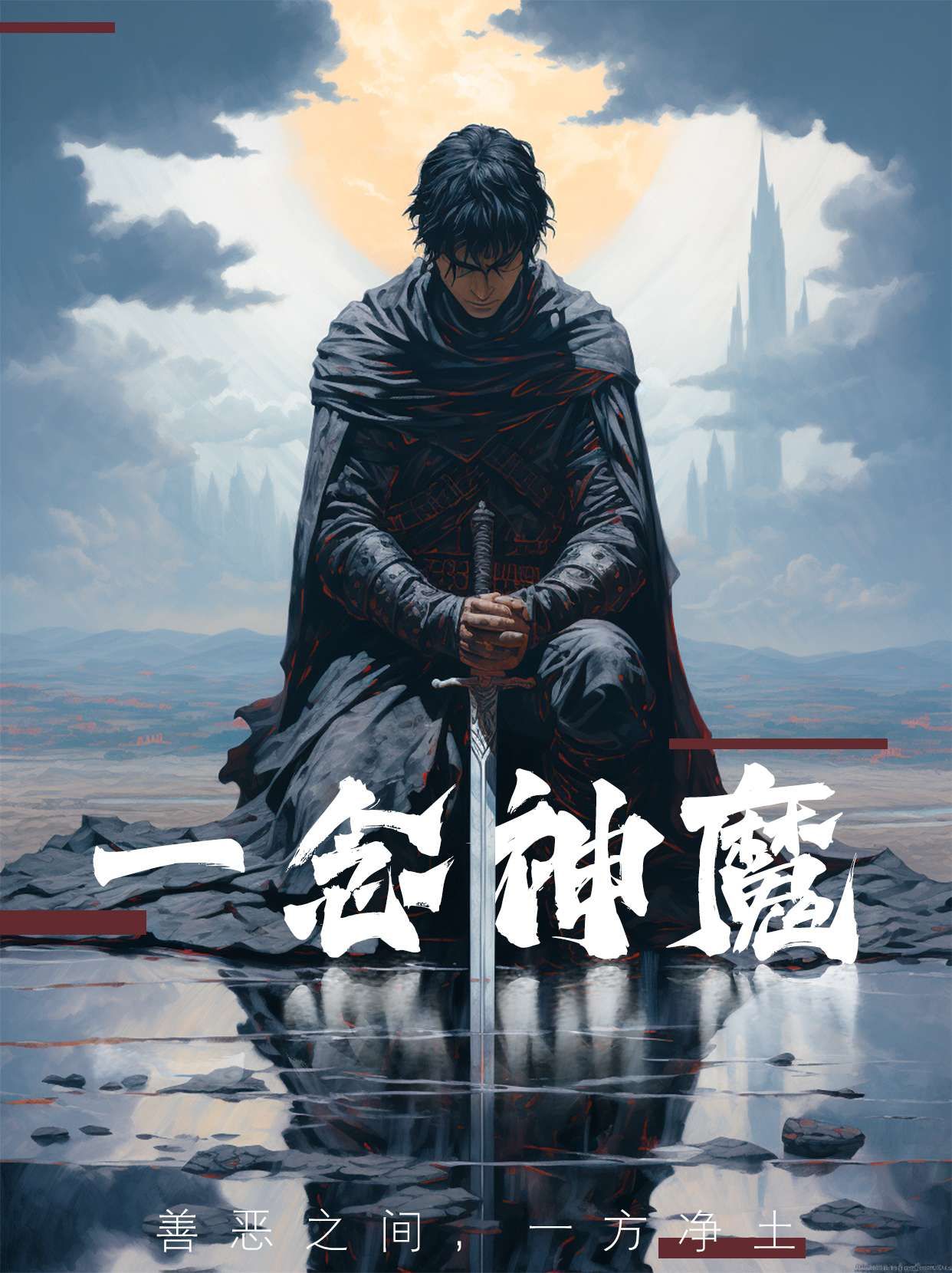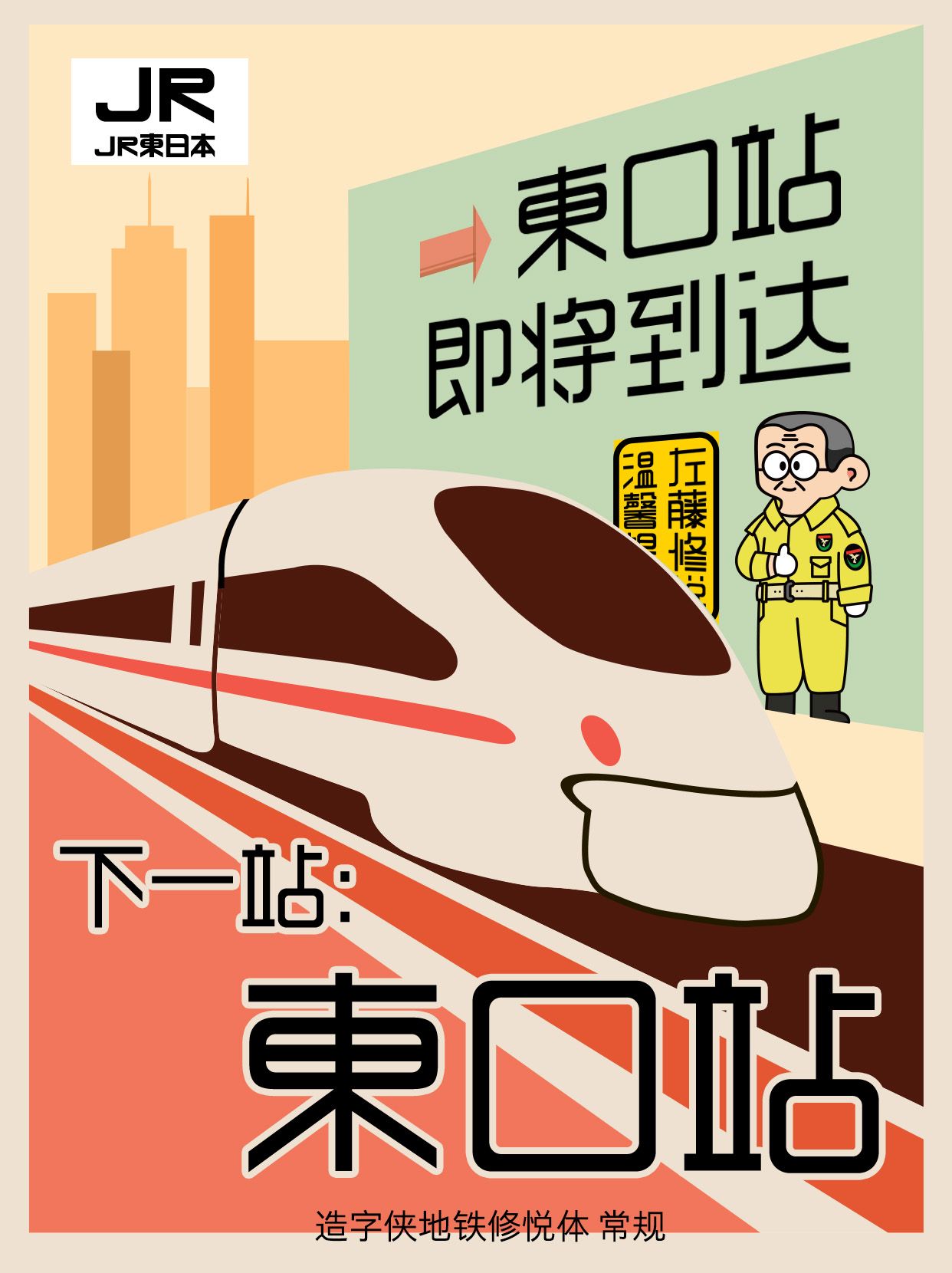
探索字体之美:四款签约精品字体推荐
励字造梦共创字库致力于与独立设计师合作,推出了一系列独具特色的原创字体。这些字体不仅展现了设计师的独特才华,同时也为用户提供了丰富的选择。下面我们将为您详细介绍四款来自励字造梦共创字库的精品字体,并探讨它们各自适用的设计场景。
1. 造字侠郝刚快乐简微黑
设计理念: 这款字体由设计师郝刚与励字造梦共创字库联合推出。它融合了西方斜体装饰风格的浪漫优雅与中国传统隶书的飘逸灵动,通过巧妙地将两者结合在一起,创造出一种独特的韵律感和节奏感。字体倾斜112度的设计,使得整体视觉效果更加动感。
应用场景: 适用于需要展现轻松愉悦氛围的设计项目,如时尚杂志、品牌宣传册、创意广告等。其独特的斜体风格,非常适合强调文本中的关键信息或用于标题设计。
2. 造字侠地铁修悦体
设计理念: 源于日本地铁保安佐藤修悦的灵感,这款字体是以胶带拼贴而成的创意黑体。它不仅体现了设计师的热情与创造力,还反映了实用主义美学,能够帮助地铁乘客更高效地找到方向。字体共5款字重,总有一款粗细适合您的设计。
应用场景: 非常适合需要强调信息清晰度和可读性的设计领域,例如交通指示系统、公共标识牌、紧急出口标志等。此外,它也适用于现代简约风格的平面设计作品。
3. 造字侠醉春风简繁苍劲
设计理念: 该字体呈现出自由率真、活泼灵动的特点。单字结构周正而不失松弛,点画圆润,笔画间过渡自然,形成一种独特的字形风貌。
应用场景: 适合于那些追求自然和谐美感的设计项目,比如儿童图书、绘本封面、艺术海报等。它的亲和力和活力能够吸引更多年轻读者的眼球。
4. 造字侠伏魔简繁传神
设计理念: 这是一款笔墨浓厚、粗细对比鲜明的字体。字体结构中正,笔画特点明显且夸张,具有强烈的视觉冲击力,适合表达力量与激情的主题。
应用场景: 适用于需要展现强烈个性和冲击力的设计场合,如游戏界面、电影海报、运动品牌宣传等。其大胆而有力的风格,能够有效吸引目标受众的注意力。
励字造梦共创字库的每一款字体都凝聚了设计师的心血与智慧,不仅满足了不同设计需求,更为设计师们提供了广阔的创作空间。希望上述推荐能帮助您在实际工作中更好地选择合适的字体,从而达到最佳的设计效果。